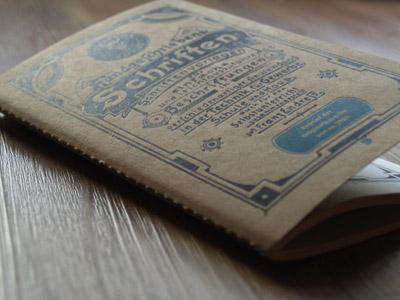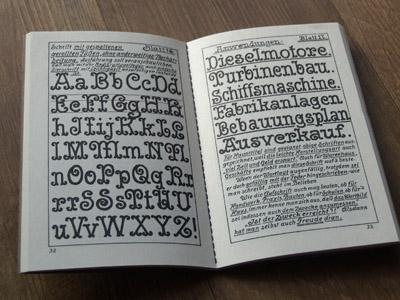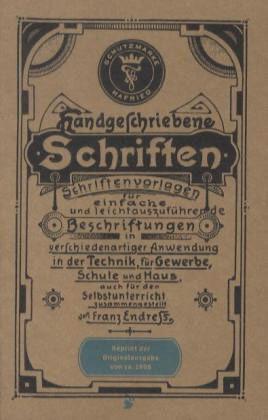
›Handgeschrieben Schriften‹ ist ein Reprint eines Heftes, das 1905 als Teil einer Schriftenreihe zu Typografie erschien. Als Flohmarktfundstück gelang es in den Hermann-Schmidt-Verlag und geriet in Vergessenheit. Zum Glück wurde es beim Aufräumen von Karin und Bertram Schmidt-Friderichs wieder entdeckt und neu verlegt.
Auf den 64 engbeschriebenen Seiten werden diverse Schriften vorgestellt, die mit kurzen Reimmerksätzen erläutert werden.
»Den freien Raum, – gemeint sind Lücken, – muß man recht schön zusammenrücken.«
Im Prinzip ist es ein Schreib- und Schriftvorlagenbuch wie viele andere auch aus der Zeit. Aber allein die hochwertige Ausstattung und Verarbeitung des Reprints machen dieses Büchlein zu einem Kleinod.